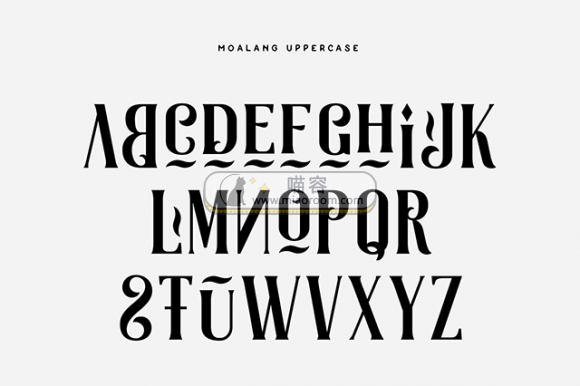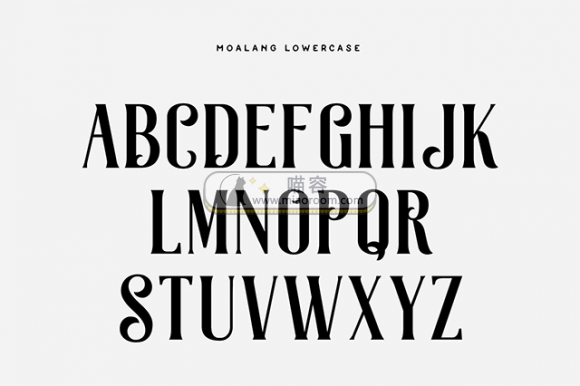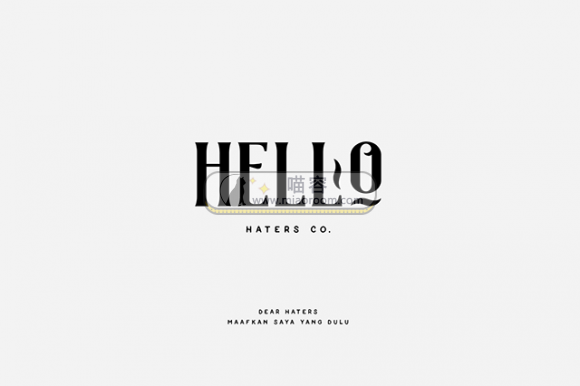
[系统字体] 一款装饰性极强的字体——Moalang 资源介绍参数 资源类别: 精美字体 如遇问题: 联系客服/留言反馈 下载地址: 前往下载 精美字体 21年1月19日 编辑 前往下载 喵容发布2号 取消关注 关注 私信 今天分享的是一款装饰性非常强的一款字体——Moalang。它由印度尼西亚的字体设计师Agga Swist’blnk设计并且免费用于个人和商业用途! 相关文章: [系统字体] 一款“狂野”风格字体系列:本文介绍的字体——Sonder是一款适用于徽标设计和大型游戏的字体。它有serif和sans-serif版本(即衬线字体和无衬线字体),同时它包括了两个样式(粗糙和常规)。该字体免费个人使用,商用需要购买哦! 下载 …... [系统字体] 具有特殊边缘的无衬线字体:今天分享的是字体叫做Brisk Pro,它具有非常特殊的边缘特征,在海报制作或者logo设计中非常实用。需要的朋友可以到文末下载哦! 下载权限查看 ¥ 免费下载 评论并刷新后下载 登录后下载 查看演示 {{attr.na …... [系统字体] 具有现代简约感的字体——axton:Axton是一款令人难以置信的圆润无衬线字体,具有现代和简约的感觉。它能让我们的作品脱颖而出。需要的朋友可以到文末进行下载哦! 下载权限查看 ¥ 免费下载 评论并刷新后下载 登录后下载 查看演示 {{attr. …... [系统字体] 美观独特的字体:wish:Wish字体具有独特有趣的波浪笔触,非常适用于品牌,标题,服装,海报,邀请函设计等等。 喵容——wish字体1喵容——wish字体2 下载权限查看 ¥ 免费下载 评论并刷新后下载 登录后下载 查看演示 {{attr.name}}: …... [系统字体] 现代简约字体 PEENU字体:资源名称 PEENU 资源大小 279kb 资源格式 ttf、png 资源简介 Peenu是一种免费的大写字体,由印度年轻UI和平面设计师Nitish Kumar设计和发布。Peenu受Sharp Paper Cuts的启发,它是海报,传单,电影片头等制 …... [系统字体]现代手写字体—GUTHERS:资源描述 字体 资源名称 现代手写字体—GUTHERS 资源格式 ttf 资源大小 385kb 资源简介 GUTHERS是一个单线脚本字体。印刷,网络,品牌,广告,杂志,产品,包装,标签等的完美选择。免费供个人使用! 喵容—— …... 喵容——Moalang字体1喵容——Moalang字体2 下载权限查看 ¥ 免费下载 评论并刷新后下载 登录后下载 查看演示 {{attr.name}}: 您当前的等级为 登录后免费下载登录 小黑屋反思中,不准下载! 评论后刷新页面下载评论 支付¥以后下载 请先登录 您今天的下载次数(次)用完了,请明天再来 支付积分以后下载立即支付 支付以后下载立即支付 您当前的用户组不允许下载升级会员 您已获得下载权限 您可以每天下载资源次,今日剩余次 声明:本文为原创作品,版权归作者所有。未经许可,不得转载或用于任何商业用途。如若本站内容侵犯了原著者的合法权益,可联系我们进行处理。 给TA打赏 共{{data.count}}人 人已打赏 moalang字体下载